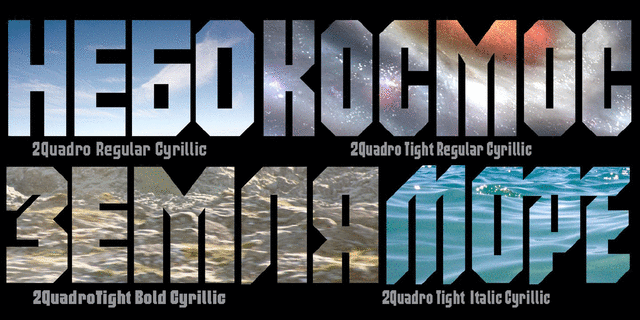
Шрифт разработан в фирме Double Alex Font Studio в 1995 году (дизайнер Алексей Чекулаев) по мотивам рисунков шрифта Aurora фирмы Agfa.
высокий, монотонный, устойчивый, тесный, сжатый, ровный, твердый, точный, сплошной, вибрирующий, полосатый, амбициозный, статичный, громкий, важный, массивный, тяжелый, техногенный, прямоугольный, заметный, яркий, активный, броский, монументальный, рациональный, мотивирующий, убедительный, стабильный, серьезный, надежный, уверенный, сильный, индустриальный, блатной